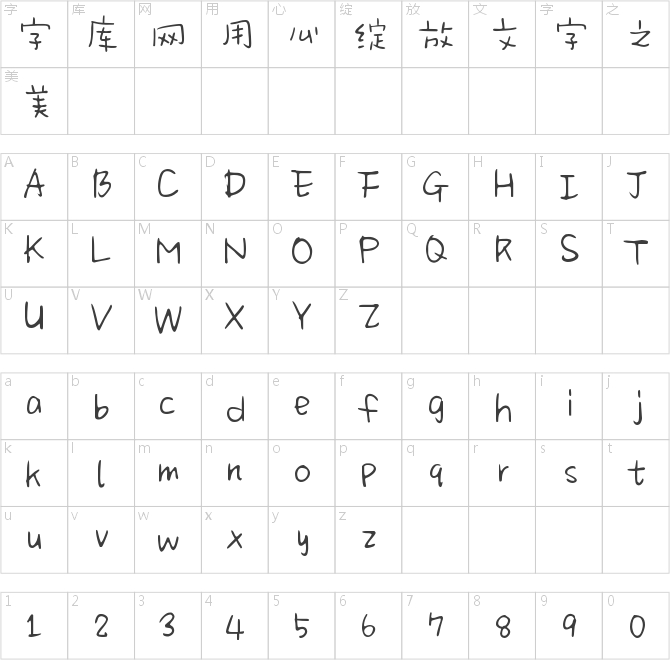
Aa188帥男團(tuán) 詳情頁(yè)
Aa188帥男團(tuán)字體字庫(kù)是一款讓人賞心悅目、百看不厭的中文字體,適合各類廣告和產(chǎn)品包裝設(shè)計(jì)應(yīng)用,字體大小5.43MB,格式為ttf字體,上傳用戶是誠(chéng)澤永信,作者/版權(quán)方為Aa字庫(kù)